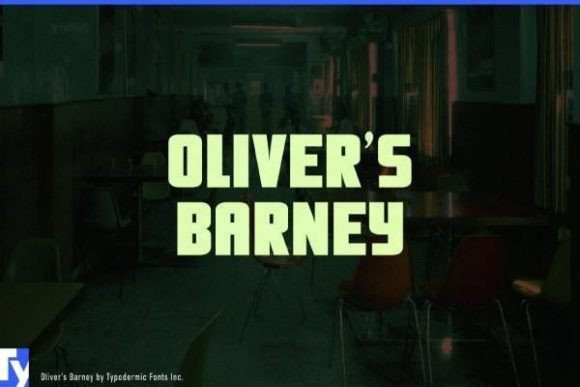
Olivers Barney
Olivers Barneyのような高品質の素材をお探しの場合、このプレミアムパッケージはクリエイティブなプロジェクトに素晴らしい選択です。
POD(オンデマンド印刷)製品、結婚式の招待状、またはソーシャルメディアのグラフィックを作成している場合でも、Olivers Barneyは理想的です。